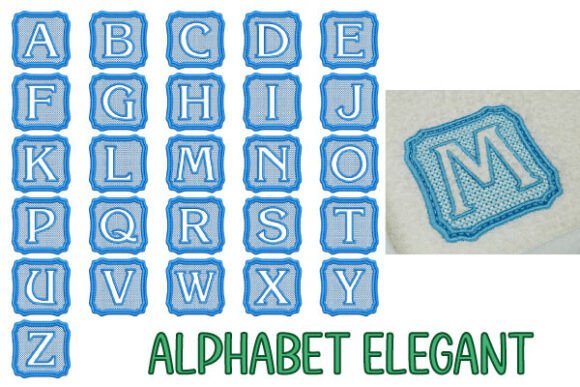
Elegant Alphabet – 7x7cm Embroidery Font
Được chế tác với độ chính xác cao, Elegant Alphabet – 7x7cm Embroidery Font cung cấp các vector sạch, kiểu chữ mượt mà và giấy phép thương mại để bạn yên tâm.